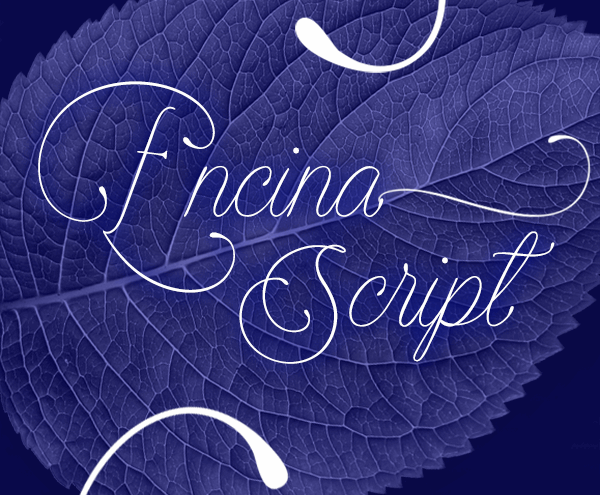
A Encina Script é uma tipografia de calligrafia formal meticulosamente projetada por Måns Grebäck. Suas linhas onduladas e finas se organiza para criar letras grandes e delicadas, tornando-a perfeitamente apropriada para o uso em magazines, convites e logotipos que requerem uma pontinha elegante. Esta fonte vem em duas versões, cada uma com alfabeto maiusculo de tamanhos diferentes, garantindo que ela funcione em todos os contextos possíveis. O recurso contextual alternativo da fonte faz com que cada palavra comece e termine naturalmente e de maneira encantadora. Esta fonte é ideal para designers buscando adicionar um toque sofisticado a seus projetos visuais, seja uma publicação ou uma identidade visual.